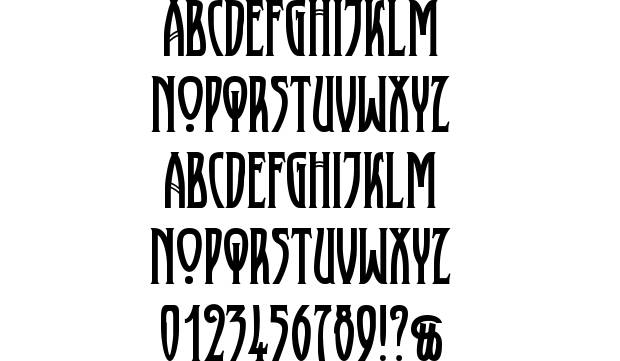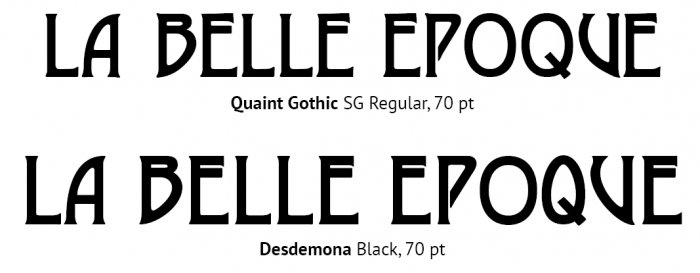
La Belle Epoque...
manchmal weiß man genau, dass man eine Schrift kennt, sie evtl. sogar im eigenen Fundus hat - und kommt trotzdem nicht darauf wie sie heißt. Und findet sie folglich nicht... Genau das passiert mir gerade im Falle des angehängten Schriftbeispiels   "La Belle Epoque". Es stammt vom Ausstellungskatalog des Museum Of Modern Art in N.Y. Kennt jemand die Schrift, weiß ihren  Namen? Über Eure kollegiale Hilfe würde ich mich sehr freuen!
O und Q sehen in der Quaint Gothic seltsam aus. Zumindest das Q passt in der Vorlage deutlich besser zum Schriftduktus.
hier aus meinen Notizen:
Typeface: Quaint Gothic SG
Designer: Jim Spiece
Year:  1900,2002
Publisher: Spiece Graphics
Additional alternate characters provided.Based on the Quaint Series from the Dickinson Type
Foundry in Boston USA circa 1900. Also known as Desdemona by the K.K. Hof & K. Brendler Foundry
War ein interessanter Hinweis auf das im Gegensatz zur New Yorker Vorlage unterschiedliche O und Q. Habe in meinem Fundus sowohl die Quaint Gothic als auch die Desdemona-Variante und natürlich sofort die Unterschiede gecheckt... Das Ergebnis füge ich zum Vergleich ein. Werde wohl die Desdemona nehmen und das O ein wenig modifizieren - dann passt's...